Absatzzeichen (¶)
Das Absatzeichen (¶) ist ein Sonderzeichen, das in der Regel das Ende eines Absatzes eines Textes markiert; Zeichen, das in Textverarbeitungsprogrammen oder Desktop Publishing Software (DTP) im »Layoutmodus« ein Absatzende bzw. Zeilenende kennzeichnet; Absatzmarke; Absatzendzeichen; Pilcrow-Zeichen.
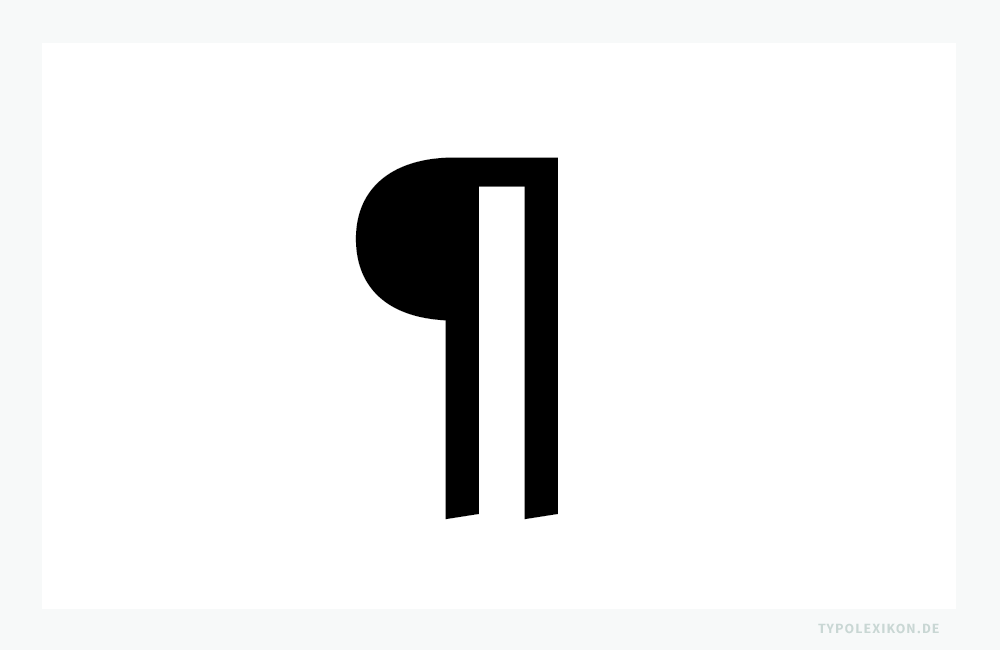
In Textverarbeitungsprogrammen, z.B. Microsoft Word ® oder Pages von Apple ®, oder Desktop Publishing Software (DTP), z.B. Affinity Publisher ® von Serif ®, InDesign ® von Adobe ® oder QuarkXpress ® von Quark ®, wird im Layoutmodus das Absatzzeichen als Formatierungszeichen (Steuerzeichen) für den manuellen Umbruch einer Zeile oder Absatzes (Absatzumbruch, Zeilenschalter) verwendet. Formatierungszeichen sind standardmäßig allerdings nicht sichtbar. Man kann diese Sonderzeichen am Bildschirm erst dann sehen, wenn der jeweilige »Layoutmodus« des Programms aktiviert wurde; In der Regel wird dann mit dem ¶-Zeichen ein Absatzende bzw. ein Zeilenende symbolisiert.
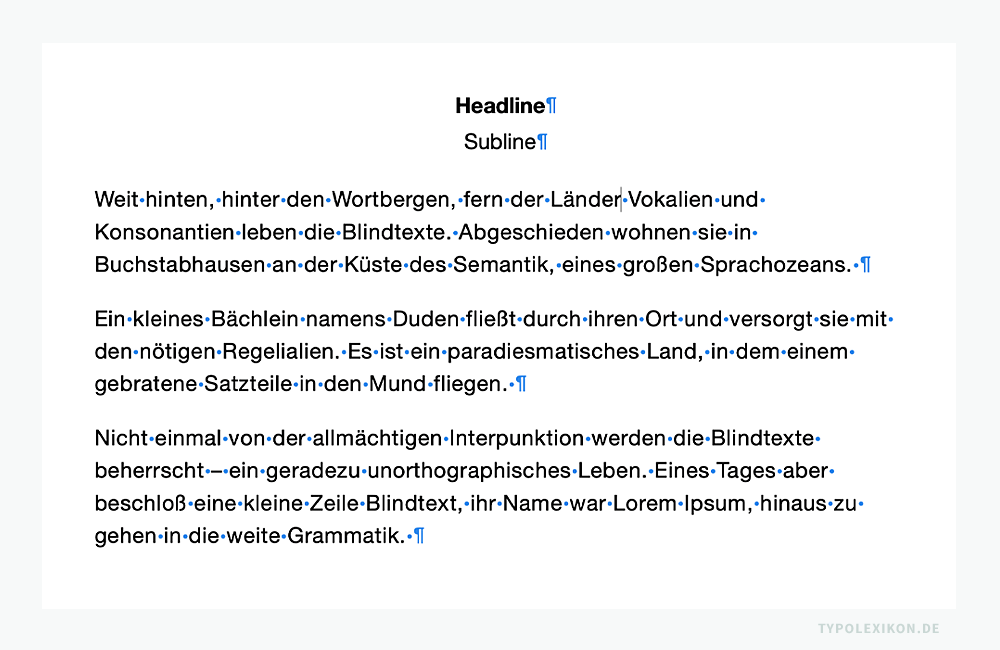
Codierungen für das ¶-Zeichen:
Unicode (Pilcrow Sign) U+00B6 HTML-Entität: ¶ ¶ ¶ UTF-8-Kodierung: 0xC2 0xB6 UTF-16-Kodierung: 0x00B6 UTF-32-Kodierung: 0x000000B6
Ursprünglich ist das Absatzzeichen ein Alinea, das bereits in der Kalligrafie und in Inkunabeln, meist in rot oder blau koloriert, 1) verwendet wurde, um Texte – anstelle von Absätzen – sinngerecht zu gliedern.
In der analogen Typografie wurde das Absatzzeichen in Manuskripten und in mit der Hand ausgezeichneten Typoskripten als Hinweis für den Setzer verwendet, damit dieser einen Absatz im Schriftsatz einfügt. In der prädigitalen Textverarbeitung wurde das Absatzzeichen auch als Konsultationszeichen in juristischen und literarischen Texten verwendet, um auf bestimmte Abschnitte oder Punkte zu verweisen.
In einigen christlichen Religionen, insbesondere in anglikanischen oder episkopalen Kirchen, wird das Absatzzeichen auf einer Tafel oder in einem Buch verwendet, um im Gottesdienst die Reihenfolge von Gebeten, Liedern und verschiedenen liturgischen Handlungen zu markieren. Diese Anweisungen sollen den Gläubigen helfen, sich während des Gottesdienstes angemessen zu verhalten, sei es durch Sitzen, Stehen, Knien oder andere Handlungen entsprechend der liturgischen Praxis ihrer jeweiligen Konfession.
| ↑1 | Beispiel: Duranti, G.: Rationale divinorum officiorum, Mainz 1459, gedruckt in der Fust-Schöffer´schen Offizin durch Peter Schöffer. |